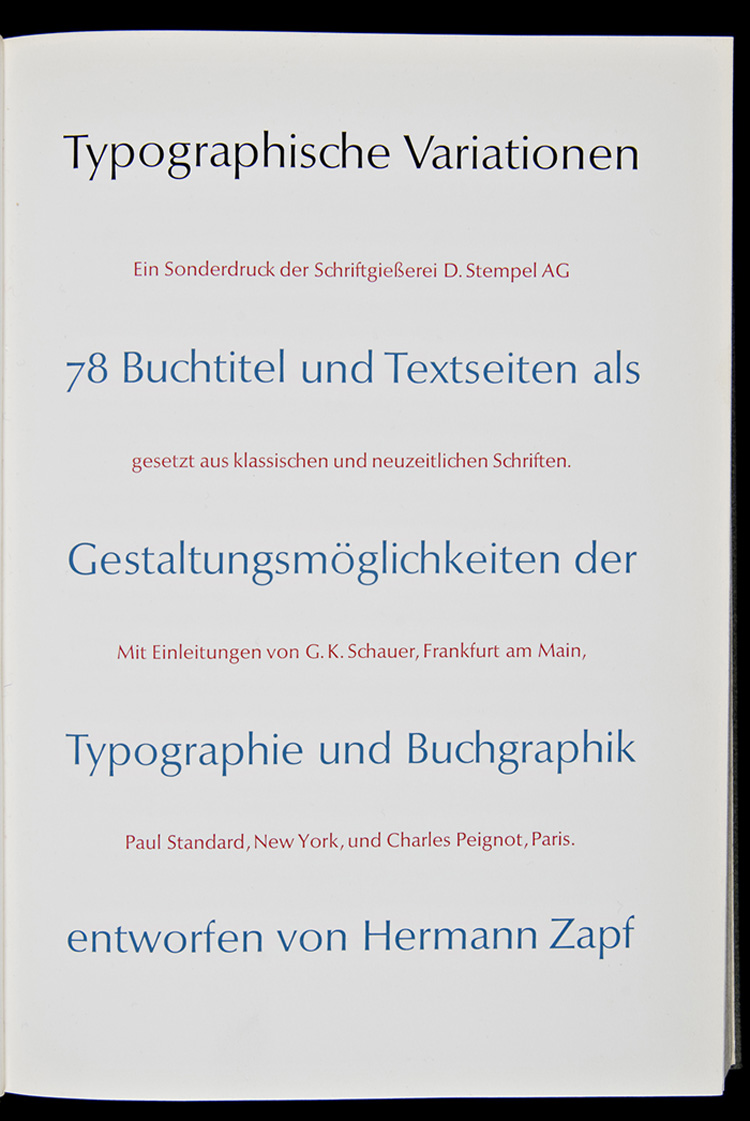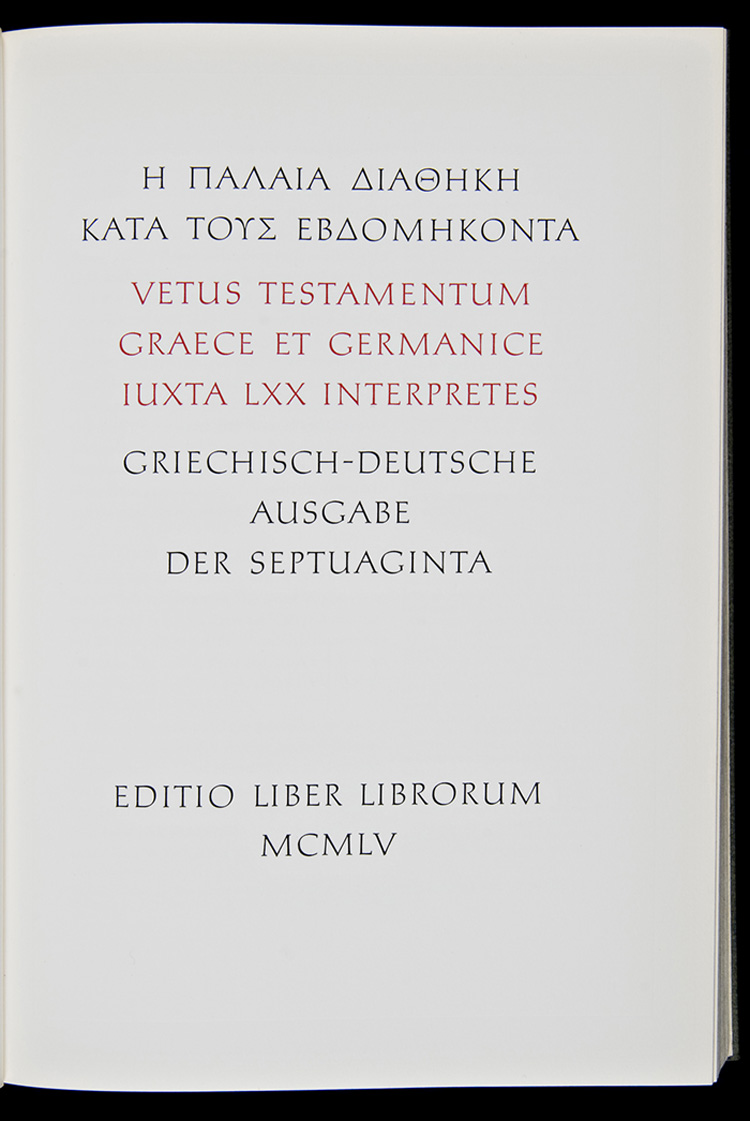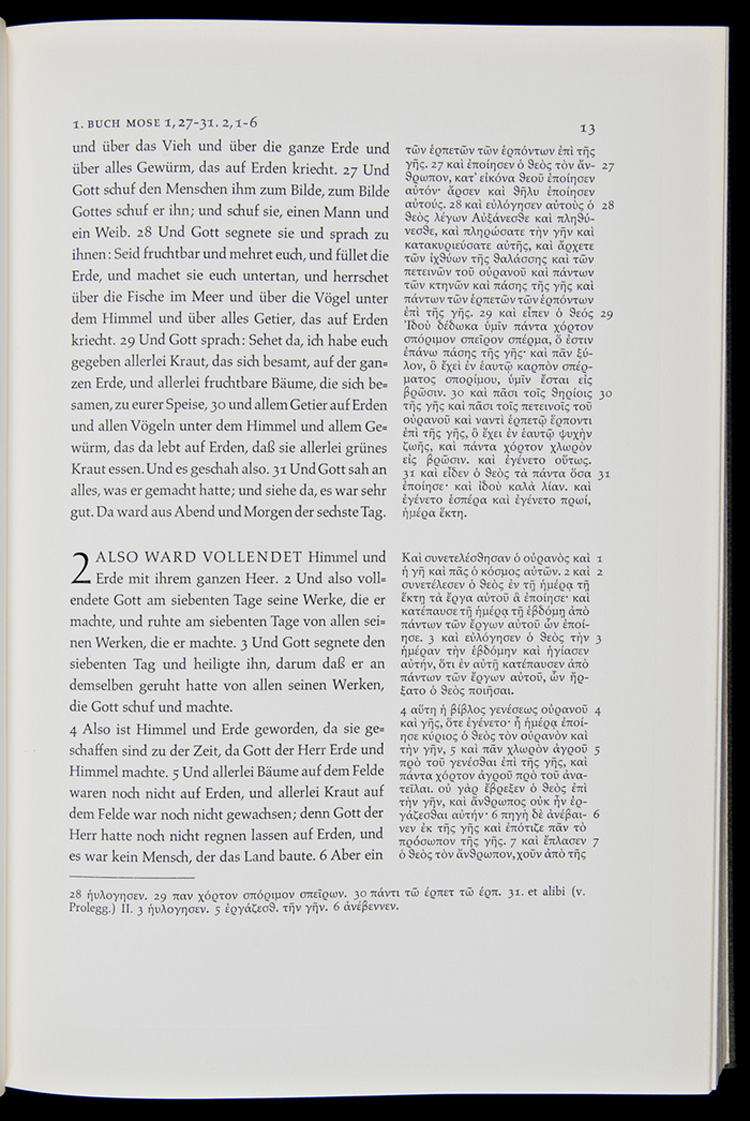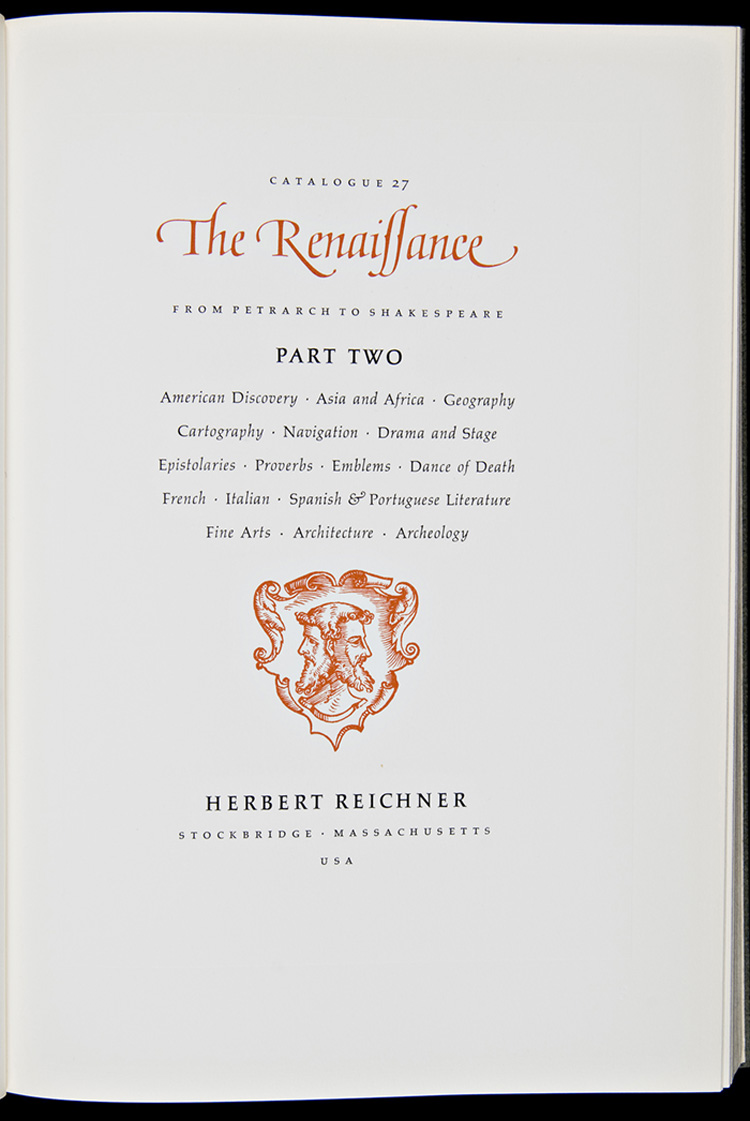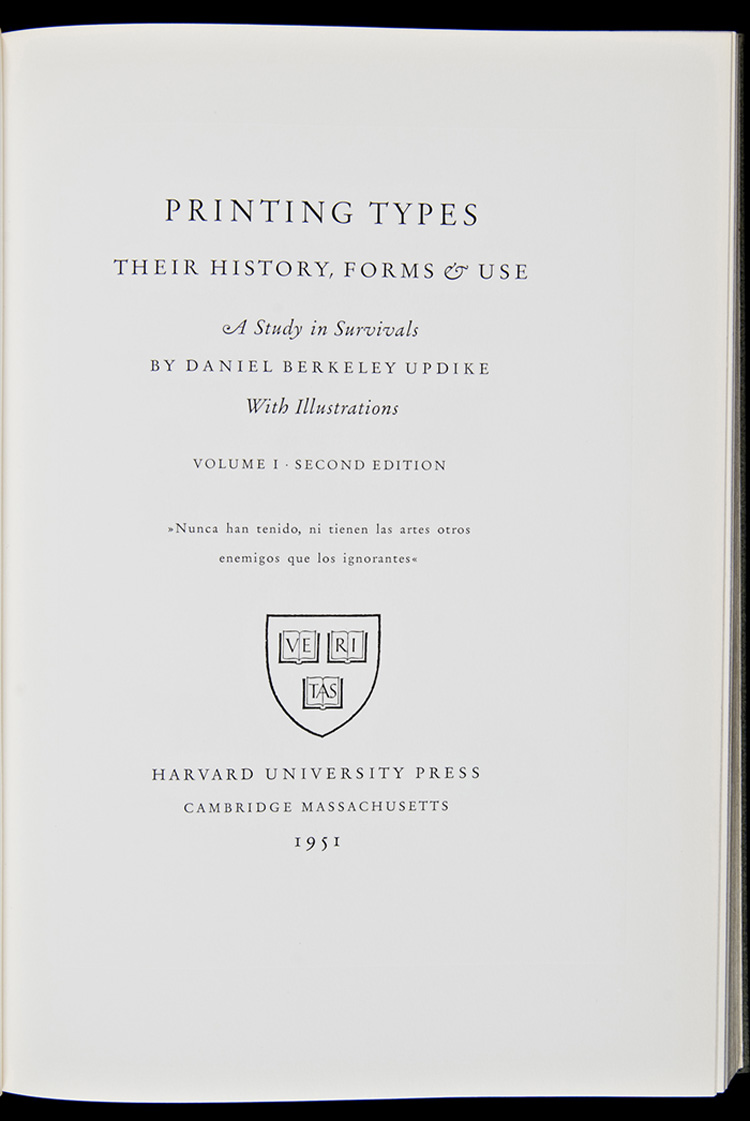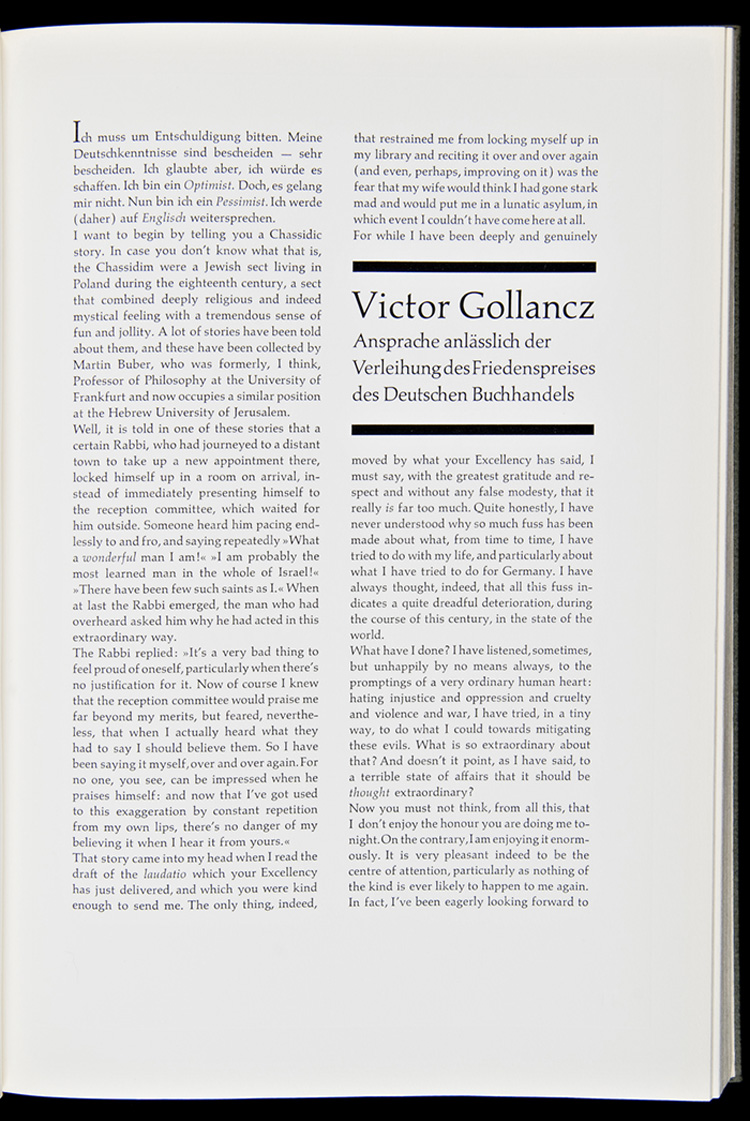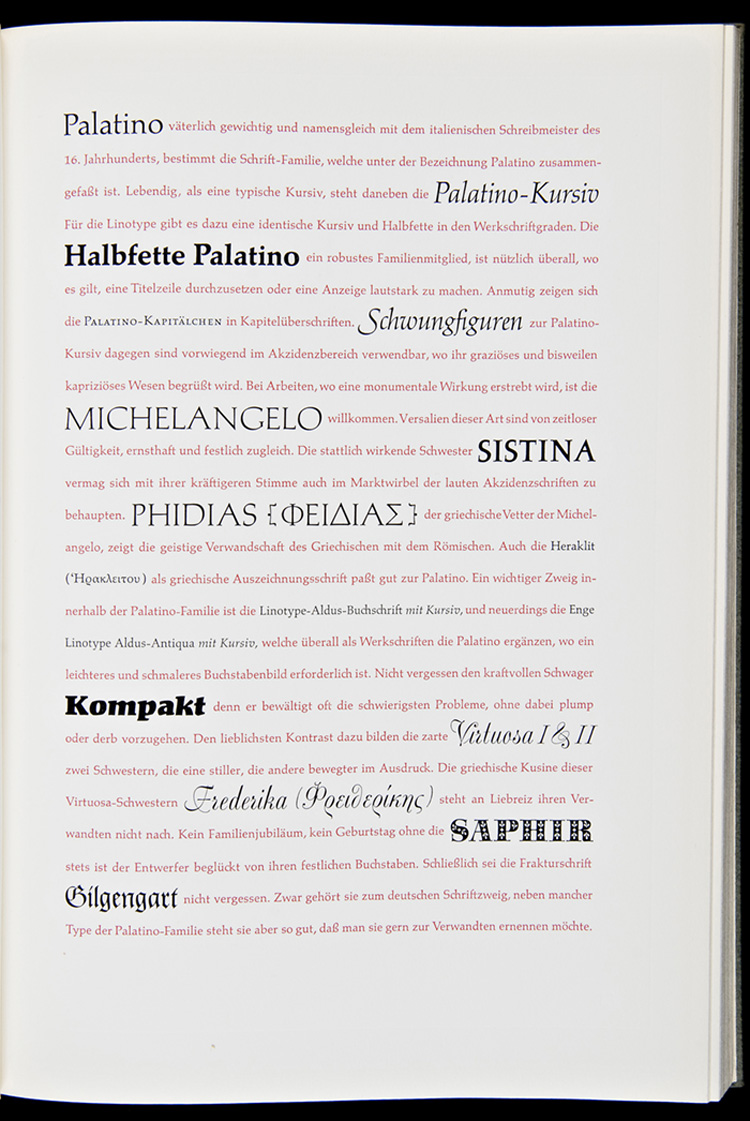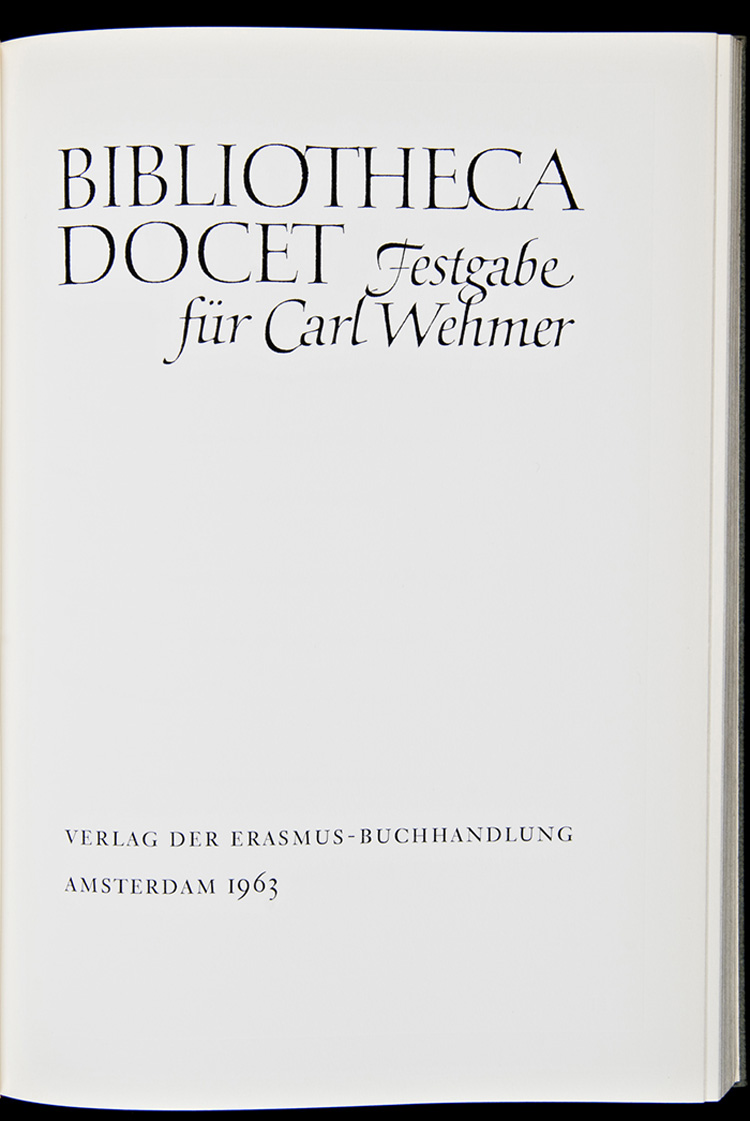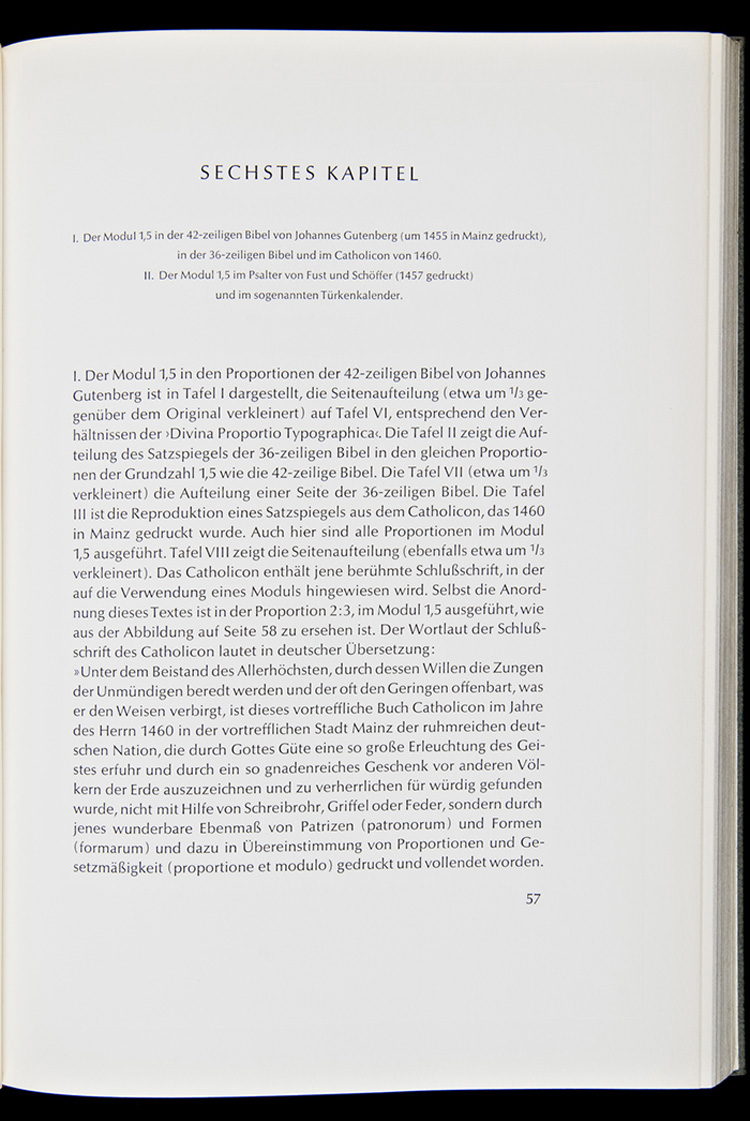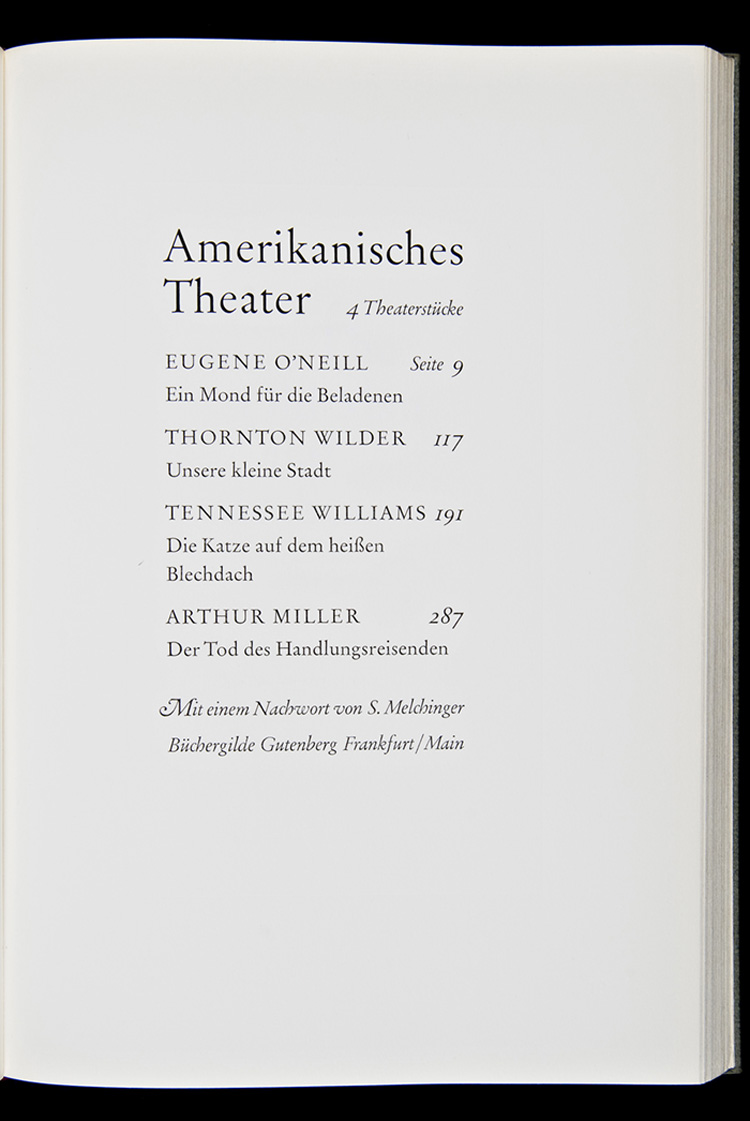
Hermann Zapf | Le deuxième Manuel Typographique au service du Livre
Consacré à l’édition, cet ouvrage à la fois expérimental mais aussi documentaire résume à lui seul le grand talent d’Hermann Zapf.
Mais le plus grand génie de Monsieur Zapf, est sans doute d’avoir été un anticonformiste avant l’heure. Ce qui aujourd’hui au nom de l’Art Contemporain est devenue la règle, Zapf va lui, l’inventer tout au long de sa vie.
Les maitres mots de Zapf sont: élégance dans la transgression, délicatesse dans le mélange des caractères, musicalité des corps associés avec une économie de moyens sans pareil, sens de l’a propos dans ces mises en page où chaque élément typographique et graphique trouve une place précise et sans équivoque, bon sens et logique d’une scénographie qui se met en permanance au service du contenu et une qualité que j’apprécie particulièrement, l’asymétrie dont joue Hermann Zapf le plus souvent possible, asymétries horizontales et verticales rompant ainsi dans le monde de l’édition avec les sacro-saintes règles de la distribution symétrique des signifiants.
Hermann Zapf nous donne au travers de ce deuxième manuel de typographie quelques pistes sérieuses pour nous aider dans la conception et la mise en page de couvertures, de pages de gardes et de textes intérieurs. Sans renier les règles traditionnels de la proportion divine, il invente cependant une liberté de ton toute empreinte d’élégance où les blancs tournants, les interlignes, et les marges obéissent avant tout à la seule contrainte de délivrer des signes cohérents et lisibles d’une mise en page au service du lecteur.